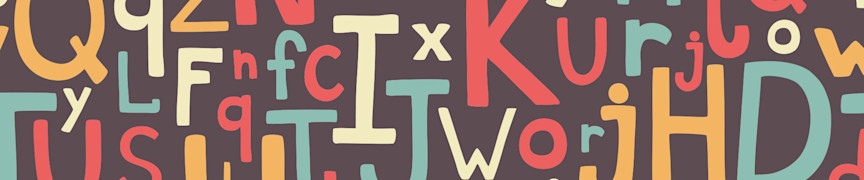
dinsdag 3 juni 2025Feestje? Open dag? Actie? Dan kan een opvallende flyer uiteraard niet ontbreken. Terugkerend element op (bijna) elke flyer is natuurlijk tekst. Hoe kun je jouw tekst er nu echt laten uitspringen? Waarmee val je op tussen al die reclame die mensen in hun handen gedrukt krijgen of op hun brievenbusmat vinden? Een opvallend lettertype doet wonderen!
Natuurlijk kennen we allemaal de grote ‘fontsites’, maar wij vinden de eigen sites van font designers veel leuker en inspirerender! In dit blog verwijs ik je naar 10 van zulk soort sites, allen met gratis fonts. Trek een uurtje uit, klik en surf er op los en ontdek wat voor prachtige fonts het internet te bieden heeft!
1. Typedepot
Typedepot is een kleine design studio, gevestigd in Bulgarije. Via haar site biedt de studio een gedeelte van haar fonts gratis aan. Wat dacht je bijvoorbeeld van font Corki (zie afbeelding)?
2. Ten By Twenty
Op de website van Ten By Twenty zijn verschillende fonts, gratis óf voor zeer kleine bedragen, te downloaden. Bovenstaande afbeelding is van font Akashi; zeer geschikt voor een moderne flyer en helemaal voor niks.
3. MyFonts.com
Via MyFonts.com kun je vele gratis fonts downloaden. Bijvoorbeeld het font Ivan van Igor Mustaev, een type designer uit Rusland.
4. Nymfont
Nymfont is de site van Lauren uit Las Vegas. Wat ooit begon als doodling tijdens lessen op school, nam toen Lauren volwassen werd steeds serieuzere vormen aan. Lauren ontwerpt inmiddels fonts en templates voor blogplatform Blogger. Haar fonts zijn te downloaden van haar site en zijn voor persoonlijk gebruik gratis. Mijn favoriete font van Lauren is Jolly, een smal en vrolijk lettertype.
5. The League of Moveable Type
Open-source project The League of Moveable Type opent op haar site met: No More Bullshit. Join the Revolution. De beweging vindt dat font designers ook wel eens iets mogen weggeven.
Oftewel: ‘It’s not always about money, sometimes it’s also about making a contribution to society, and in this case, the design community. We want more people to look at it like that: like they have a responsibility to do something good for their peers.‘ Via de site kun je verschillende mooie lettertypes downloaden. Helemaal voor noppes!
6. Blue Vinyl Fonts
Op Blue Vinyl Fonts kun je ook weer gratis fonts downloaden. Dit keer zowel voor persoonlijk als zakelijk gebruik. Een gedeelte van de fonts bestaat volledig uit afbeeldingen, zoals font Love Romance (zie afbeelding).
7. Characters Font Foundry
Fonts van Hollandse bodem! Characters Font Foundry is van de Nederlander René Verkaart, die veel van zijn fonts tijdens zijn vakanties ontwerpt. René biedt enkele van zijn fonts helemaal voor niks aan. Neem bijvoorbeeld font Nantua Roman, geïnspireerd door het Russische constructivisme.
8. HvD Fonts
Het Duitse HvD Fonts biedt via haar site verschillende, wat grovere, gratis lettertypen, aan. Super geschikt voor op een flyer! Neem bijvoorbeeld font Poster (zie afbeelding).
9. Rodrigo de Carvalho
Font Comets - Rodrigo de Carvalho
Font Garagin Rock van ontwerper Rodrigo de Carvalho is echt bijzonder; anders dan veel andere fonts die je online tegen komt!
10. Andreas Leonidou
Font Matey v2 - Andreas Leonidou
De Cypriotische font ontwerper Andreas Leonidou heeft in zijn online portfolio verschillende gratis fonts ter beschikking gesteld. Een font dat zeker niet misstaat op een folder is Matey v2.